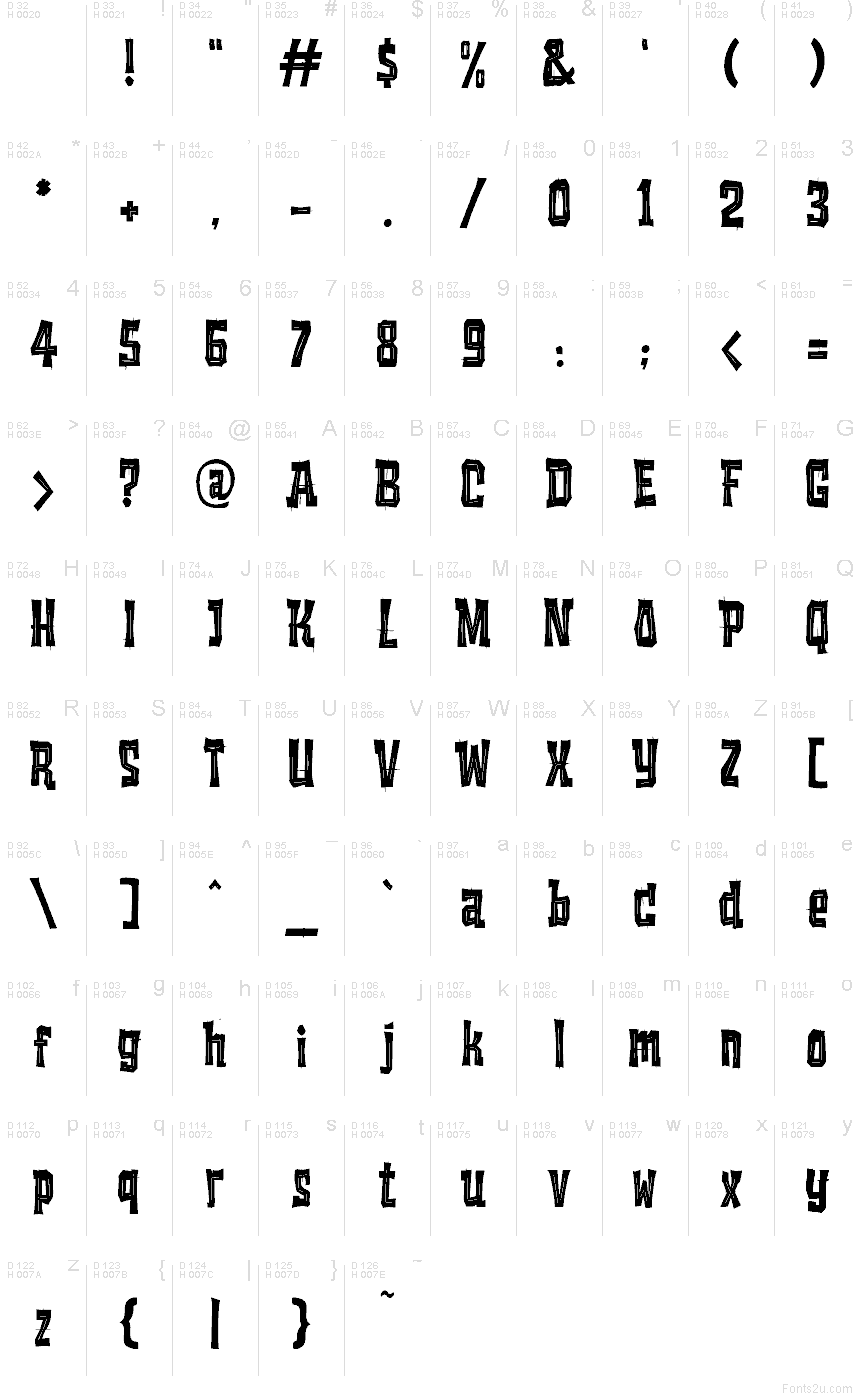
The Bandit and the Lone Rider é uma fonte display gratuita em estilo Western da BlackFridayFont, construída com letras altas e irregulares que possuem a autoridade bruta das placas talhadas à mão da era da Fronteira. As formas pesadas tipo slab, as bordas irregulares e as junções marcadas criam um ritmo arrojado de tipos de madeira, sem depender de floreios ornamentais.
Adapta-se naturalmente a cartazes de "procurado", identidade visual de saloons, capas de álbuns de música roots, títulos de jogos de faroeste e embalagens rústicas de alimentos ou bebidas. Como fonte gratuita, também funciona muito bem para títulos curtos, onde as variações exageradas de altura e as siluetas robustas conseguem sustentar a composição por si mesmas.